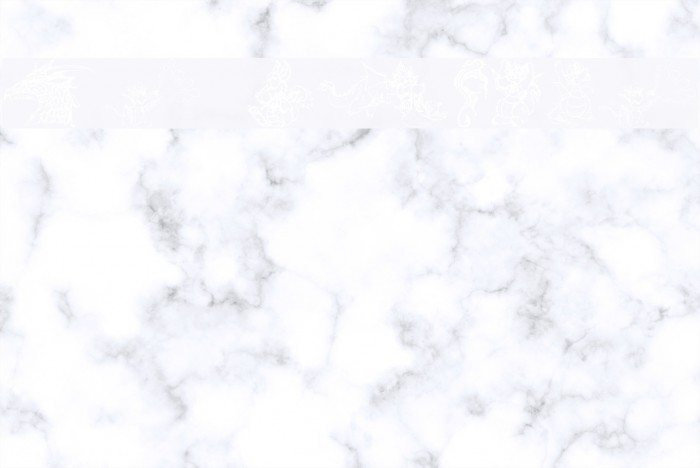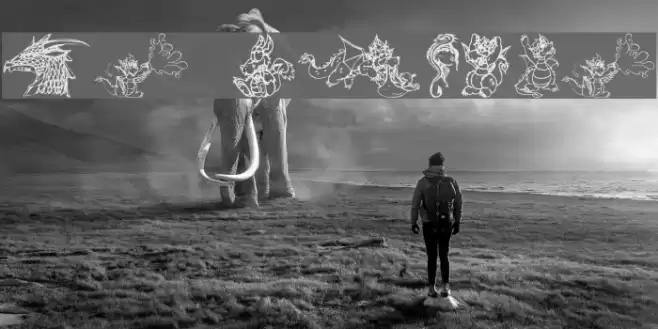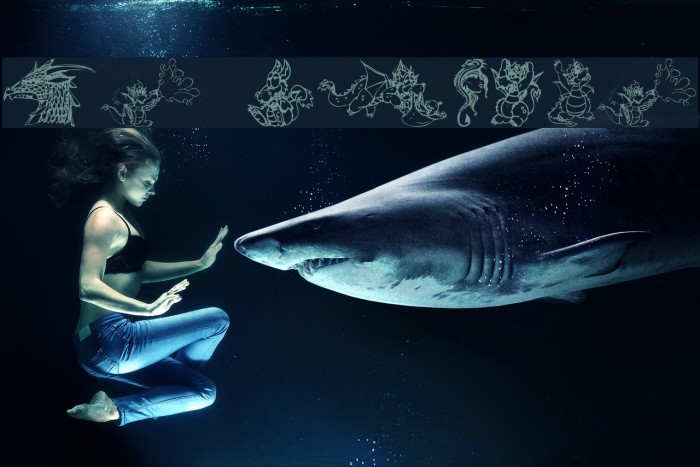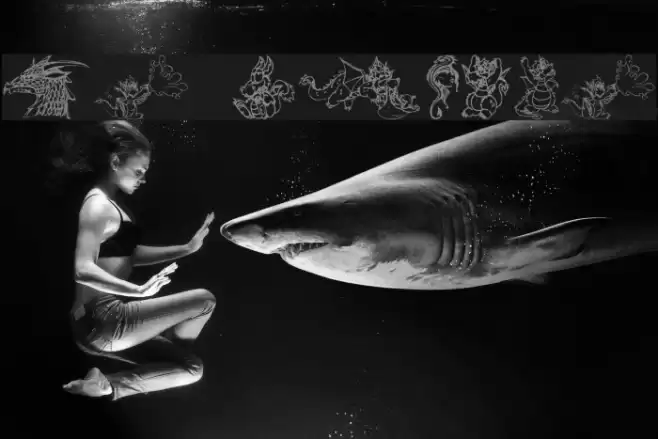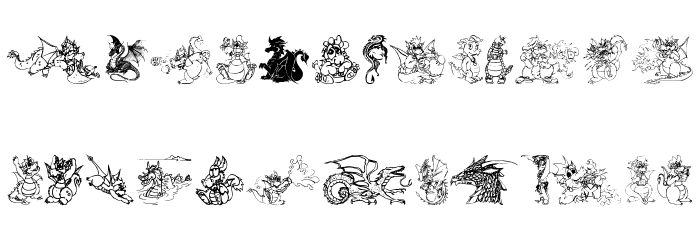
Ev's Dragons Font
| Gesamtstil | Decorative, Whimsical, Playful |
| Anwendungsfall | Logos, Posters, Themed Headlines, Invitations |
| Vorgeschlagene Projekte | Children’s books, fantasy-themed party invitations, game titles, posters, playful branding. |